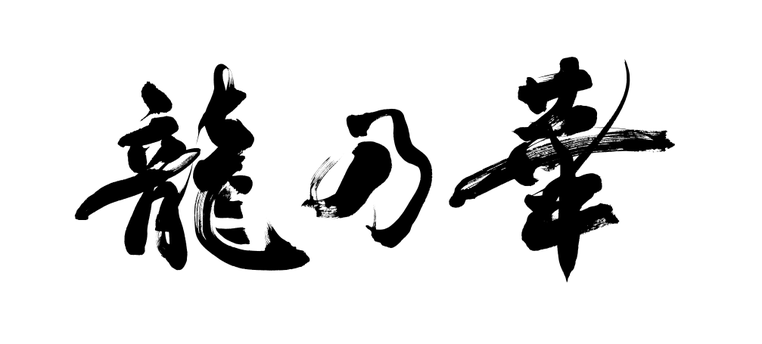
焼肉店看板の筆文字制作|書家に依頼・注文するならお任せください! 参考イメージ画像(白黒反転) 焼肉店様の看板の筆文字制作 字の方向性 高級 ★★★★★ 正統派 ★☆☆☆☆ 迫力・力強さ ★★★☆☆ 大衆性・親しみやすさ ☆☆☆☆☆ 味わい系・素朴系 ☆☆☆☆☆ 個性的・オリジナリティ ★★★☆☆ 美人系・艶 ★☆☆☆☆ 流れ・しなやかさ ★★☆☆☆ 静寂 ☆☆☆☆☆ 線の太さ 中くらい~やや太めあたりの線をメインにして、所々に細い線とかなり太めの線を入れています。 tagPlaceholderカテゴリ: 筆文字オーダーメイド